Iran sorgt aktuell immer wieder für Negativ-Schlagzeilen. Atomkonflikt, Israel-Politik, Holocaust-Debatte – die politische Lage ist angespannt. Das Bild, das die Medien hierzulande von der islamischen Republik zeichnen, fokussiert den Blick auf diese problematische, Ängste schürende Seite.
Gerade in Anbetracht dieser Situation erscheint es besonders wichtig, eine Brücke zu schlagen und den Blick auf Iran zu erweitern.
Vom 30. April bis zum 10. Mai 2007 veranstaltet die Hochschule für Gestaltung und Kunst in Basel eine neue Vortragsreihe zum Thema »Iranian Typography«. Ausserdem gibt es dazu bereits eine gut gestaltete und sehr informative Website zu den Designern: Majid Abbasi, Farzad Adibi, Tahamtan Aminian, Mostafa Assadollahi, Mohammad Ehsaei, Ebrahim Haghighi, Pedram Harby, Saed Meshki, Morteza Momayez, Alireza Mostafazadeh, Masoud Nejabati, Mehdi Saeedi, Bijan Sayfouri und Ghobad Shiva.
In diesem Kontext möchte ich hinweisen auf das letztjährige Freiburger Ausstellungs-Projekt iran.com und den »ersten« iranischen Weblog-Aktivisten Hossein Derakhshan.
Das Internet mit der Parallelwelt der Weblogs ist für viele Iraner ein Forum »freier Kommunikation« über kulturelle und politische Themen. Und damit ein Netzwerk neuer Ideen, welches sich staatlicher Kontrolle entzieht. Die iranischen Blogger sprechen mit Witz, Poesie und Zorn über ihre Konflikte ... über Musik, Liebe, Design und über die Trauer um verschundene Helden.
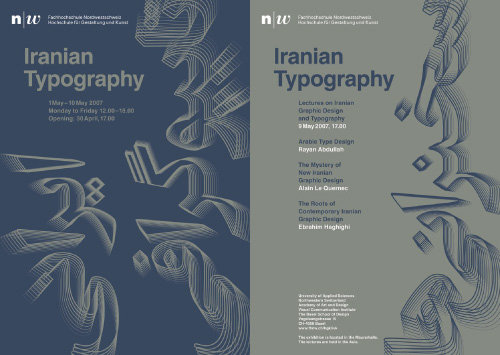
iran- oder islamismusbashing (gerne alles mal pauschal unter general- & schnellem extremismus- bzw. terrorverdacht gleichgesetzt) ist wirklich zum kotzen verbreitet.
insofern sehr zu begrüssen, was die baseler jetzt veranstalten und einer (westlichen) öffentlichkeit zugänglich machen.
sehr schön!
Typografie scheint im Iran eine reine Männersache zu sein. Komisch?
typografie scheint in deutschland oder überhaupt in sogenannten westlichen kulturen eine ganz schöne männersache zu sein. komisch?
Immerhin hat das Abendland typographische Frauen. "Mann" muss halt genau hinsehen. Vielleicht ist Typografie in Asien, Lateinamerika oder sonst wo eher Frauensache, lieber Flo, ich weiss es nicht.
Aber das ist hier nicht Gegenstand. Vielmehr geht es darum, ob über Schrift-/Kultur Iran-Aufklärung betrieben werden kann, wenn das, nach unseren Maßstäben, unterdrückte Geschlecht nicht daran Teil hat.
Die Ausstellung und Website erweitert natürlich unseren Blick, lässt uns blicken in eine alte, wunderschöne Schriftkultur aber holt uns auch schnell wieder auf den Boden der Tatsachen zurück.
ob es hierbei um iran-aufklärung gehen soll bezweifle ich so einigermassen.
wolfgang schreibt ja oben von einem brückenschlag, und den blick auf arbeiten zu richten, die nicht wie ansonsten überwiegend europäischen und us-amerikanischen ursprungs sind ist doch ganz begrüssenswert.
natürlich muss man bei der thematik iran sehr vieles kritisieren, und dein hinweis, herr geh, ist vollkommen richtig. ich empfinde nur immer ein wenig unbehagen dabei, wenn ein «westlicher» blick auf andere kulturregionen beginnt, elemente von zurechtweisung, selbstgerechtigkeit, missionierung oder imperialismus zu enthalten, und von oben herab kommt.
damit meine ich jetzt nicht deine kommentare.
aber wenn du nur den einen satz schreibst, männersache, dann verkürzt es die veranstaltung etc. doch ein wenig, und schiebt erfreuliches in den kreis üblicher vorbehalte.
ich denke, «hier» gibt es noch jede menge zu tun, was einen einsatz für frauen angeht.
1. Trifft nicht zu.
2. Wenn schon, was dagegen einzuwenden? Sollen die iraner deswegen wieder den Teufeln Tür & Tor öffnen? Also bitte, ja!
hier noch ein designer aus iran, wurde mal in "dienacht"-magazin vorgestellt: